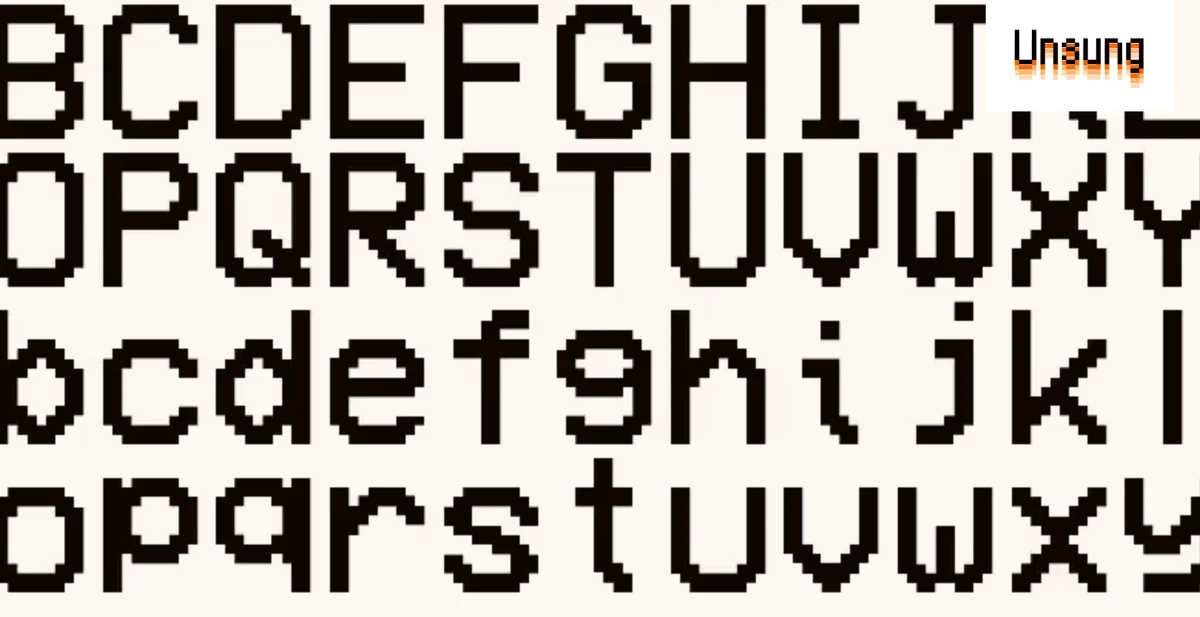
1990년대 레트로 감성을 자극하는 픽셀 폰트(Pixel Font) 디자인 트렌드 소개
가독성, 스케일링, 메트릭스(Metrics) 등 실용성을 고려한 폰트 디자인의 중요성 강조
Analog Mono와 같은 폰트가 VCR OSD Mono의 문제점을 개선하여 주목받음
Geist Pixel의 시스템 확장으로서의 접근 방식에 대한 긍정적 평가와 가독성 논쟁이 존재함
최근 픽셀 폰트가 다시 주목받으면서, 폰트 디자인의 가독성(Readability)에 대한 논의가 활발하게 진행되고 있다. 특히, 128x64 픽셀 디스플레이(Display)와 같은 제한된 환경에서 픽셀 폰트의 가독성 확보는 중요한 과제이다. 댓글에서는 폰트 제작 도구인 Font Forge를 활용하여 직접 픽셀 폰트를 제작하는 경험을 공유하며, 가독성을 높이기 위한 다양한 팁을 제시한다. 픽셀 폰트 디자인은 단순한 레트로 감성을 넘어, 사용자 인터페이스(UI)의 중요한 요소로 자리 잡고 있다.
Geist Pixel은 단순한 시각적 효과를 넘어, 시스템 확장(System Extension)으로서의 픽셀 폰트를 제시한다. 이 폰트는 다양한 뷰포트(Viewport)에서 적절한 스케일링(Scaling)을 지원하고, 기존 타이포그래피(Typography)와 조화를 이루도록 설계되었다. 댓글에서는 Geist Pixel의 실용적인 접근 방식에 대해 긍정적인 평가를 내리며, 픽셀 폰트가 실제 제품에서 어떻게 활용될 수 있는지에 대한 기대를 나타낸다. 특히, 커닝(Kerning), 메타데이터(Metadata), 추가 글리프(Glyphs) 등 폰트의 세부적인 부분까지 고려한 점을 높이 평가한다.
픽셀 폰트 디자인은 기술적인 도전 과제(Technical Challenges)를 동반한다. 폰트의 수직 메트릭스(Vertical Metrics), 커닝, 그리고 다양한 글리프(Glyphs)를 적절하게 관리하는 것은 폰트의 가독성과 시각적 일관성을 유지하는 데 필수적이다. 댓글에서는 폰트 디자인 과정에서 발생하는 문제점들을 공유하며, 폰트 제작 시 고려해야 할 사항들을 제시한다. 특히, 폰트의 스케일링(Scaling)과 다양한 환경에서의 렌더링(Rendering) 문제를 해결하기 위한 노력이 강조된다.
커뮤니티에서는 다양한 픽셀 폰트에 대한 의견을 공유하며, 각 폰트의 장단점을 비교한다. Analog Mono와 Two Slice와 같은 폰트는 디자인적 특징과 가독성 측면에서 긍정적인 평가를 받았다. 반면, Geist Pixel의 디자인에 대한 비판적인 의견도 존재하며, 폰트의 시각적인 특징과 가독성에 대한 논쟁이 벌어진다. 또한, Gohu font와 같이 특정 환경에서 뛰어난 렌더링(Rendering)을 보여주는 폰트가 소개되면서, 폰트 선택에 대한 다양한 취향을 엿볼 수 있다.